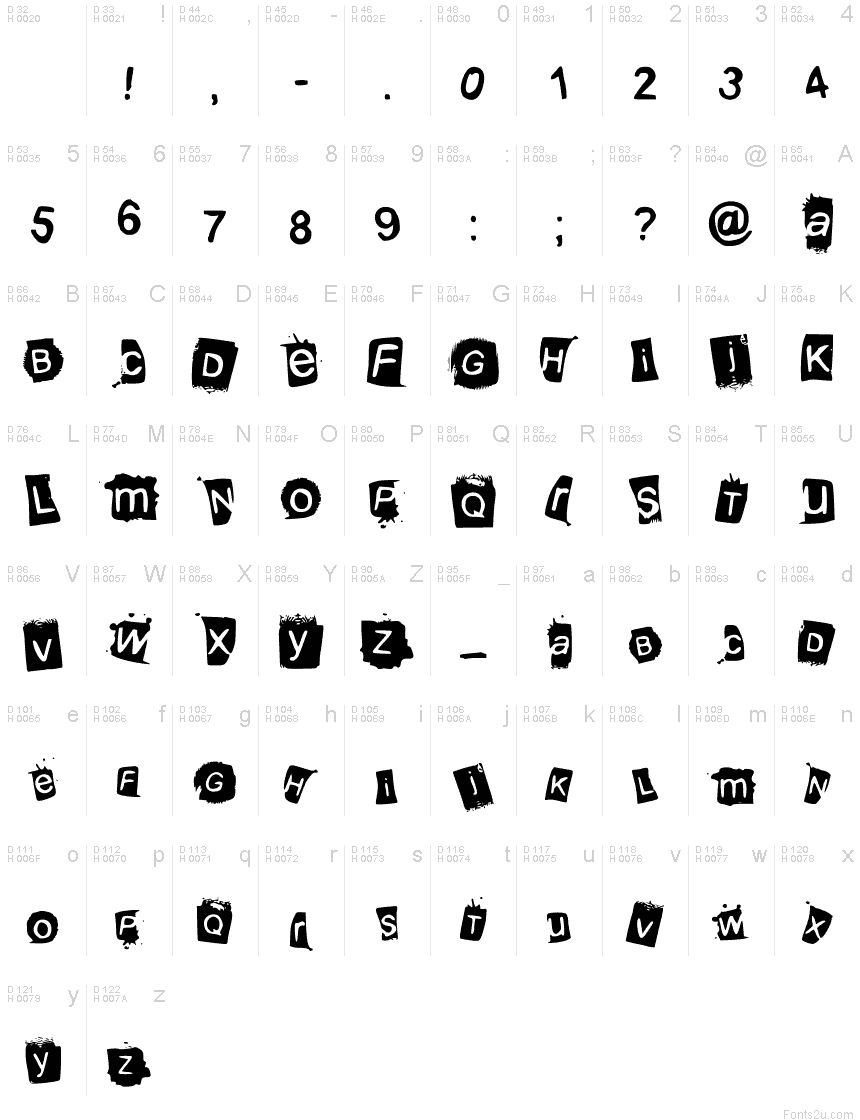
KrooKed autorstwa Davy'ego Meykensa to darmowy, zniekształcony krój typu display, zbudowany z surowych, indywidualnie uformowanych bloków. Zamknięte litery mają tępe krawędzie przypominające wycinanki z papieru, nierówne proporcje oraz celowo niedopasowaną linię bazową, która przywołuje na myśl domowe liternictwo z kolaży.
Projektanci pracujący dla odbiorców związanych z punkiem, deskorolką i kulturą DIY uznają go za odpowiedni do plakatów koncertowych i ulotek wydarzeń. Jego sklejona konstrukcja pasuje również do okładek płyt i merchandisingu sitodrukowego, zwłaszcza z fotokopiowanymi teksturami lub ręcznie wycinaną grafiką. Nieregularne bloki sprawiają, że krój ten naturalnie pasuje do motywów muzyki podziemnej i kultury ulicznej.
KrooKed